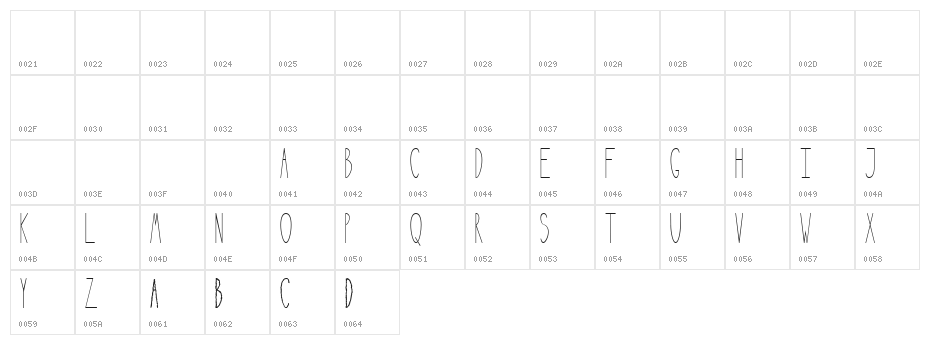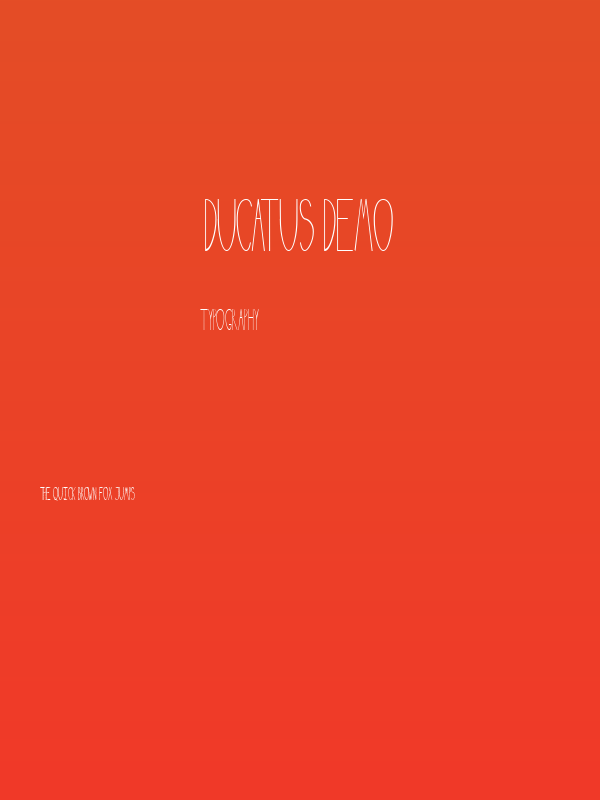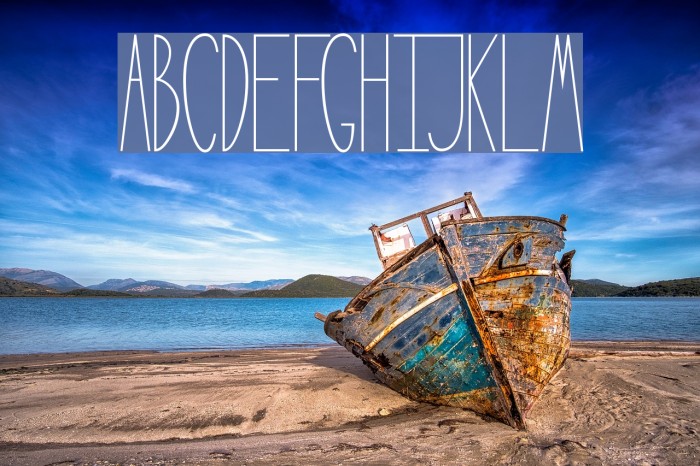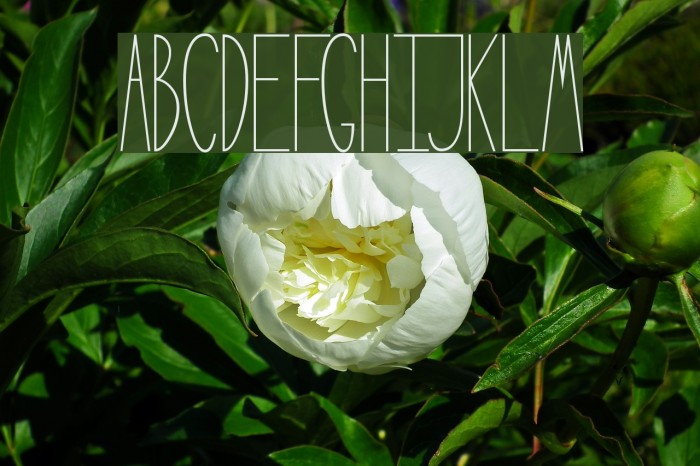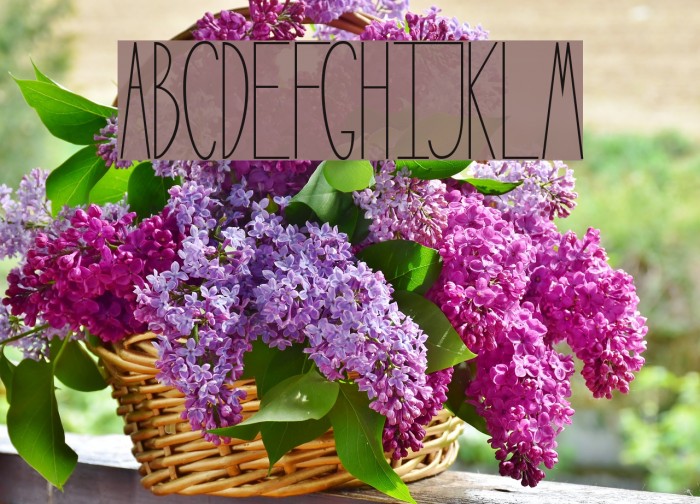
Ducatus Demo Font
| Stil general | Modern, Artistic |
| Caz de utilizare | Headlines, Branding, Posters |
| Proiecte propuse | Ideal for branding, posters, and editorial design where a mix of modern and artistic elements is desired. |